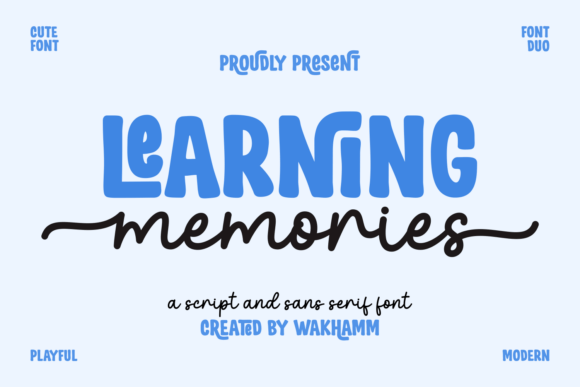
Learning Memories
Learning Memories – Uma Mistura Harmônica de Sofisticação Lúdica
Se você procura uma tipografia que una charme e design moderno, o duo Learning Memories chega como a escolha certeira. Essa combinação premium reúne um script monoline elegante com um display sans‑serif cheio de personalidade, proporcionando um visual que é ao mesmo tempo tendência e atemporal.
- Script monoline fluido: traz um toque artesanal, quase como se fosse escrito à mão, conferindo delicadeza e calor à identidade visual.
- Display sans‑serif ousado: oferece força e clareza, garantindo legibilidade em tamanhos pequenos e impacto em grandes formatos.
- Equilíbrio perfeito: a suavidade do script complementa a robustez do sans, criando uma harmonia visual que atrai tanto públicos jovens quanto corporativos.
- Versatilidade de aplicação: ideal para branding, logotipos, embalagens, posts de redes sociais e projetos criativos que necessitam de um toque amigável, porém sofisticado.
- Design atemporal: apesar de estar alinhado com as tendências atuais, a tipografia permanece relevante ao longo dos anos, evitando a necessidade de substituições frequentes.
Por que Learning Memories se destaca no mercado?
Ao escolher Learning Memories, você investe em uma identidade visual que comunica confiança e acolhimento. A combinação de script e sans‑serif permite criar hierarquias tipográficas claras: títulos impactantes com o display sans e detalhes delicados com o script, facilitando a leitura e a navegação do usuário.
Além disso, a fonte foi cuidadosamente desenvolvida para oferecer alta legibilidade em diferentes dispositivos, desde telas de smartphones até impressões em grande escala. Isso a torna a solução ideal para quem deseja consistência de marca em todos os pontos de contato.
Aplicações Ideais
- Identidade visual de startups e marcas de lifestyle.
- Embalagens de produtos artesanais ou premium.
- Campanhas de marketing digital e posts de Instagram.
- Materiais corporativos como relatórios e apresentações.
- Websites que buscam um visual moderno e acolhedor.
Learning Memories não é apenas mais uma fonte; é a ferramenta estratégica que transforma projetos criativos em experiências memoráveis. Se o seu objetivo é transmitir elegância sem esforço e profissionalismo com um toque amigável, esta combinação de tipografia é a escolha perfeita. Experimente hoje mesmo e descubra como a harmonia entre script e display pode elevar sua marca a um novo patamar.